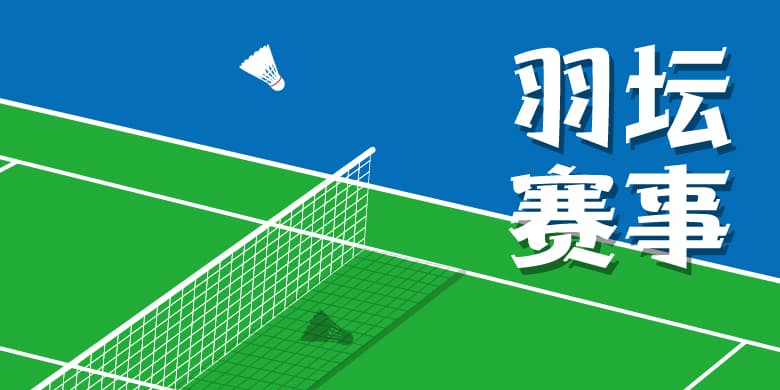
方正快盈体家族
品牌:方正字库设计师:郭炳权发行时间:2019字库编码:简繁扩展(GBK)、大陆简体(GB2312-80)分类:创意字体字体属性:精品字
设计灵感源于一款羽毛球拍的LOGO。每一个“口”形,左下角的小缺口,成为这款字的焦点和特色,适度的修饰线也为字体增添精彩。
快盈体家族含8种不同粗细字体,适合品牌饮料,体育用品,服装运动鞋的商业宣传和包装设计。